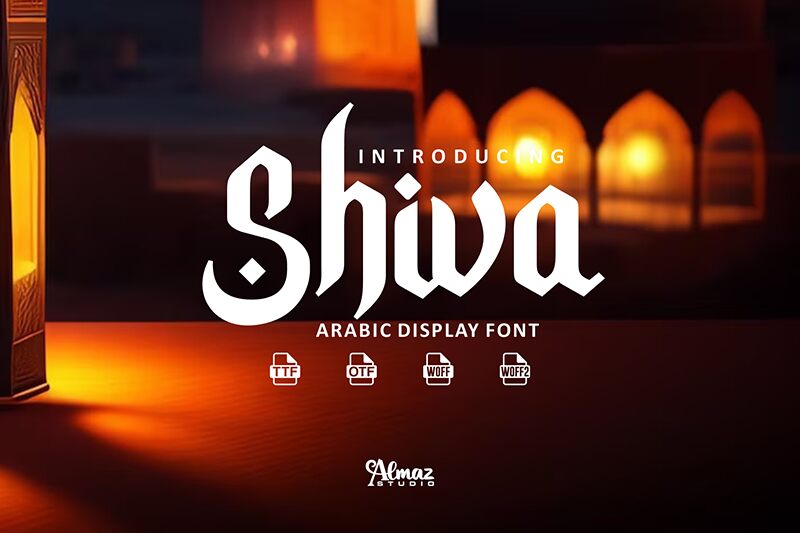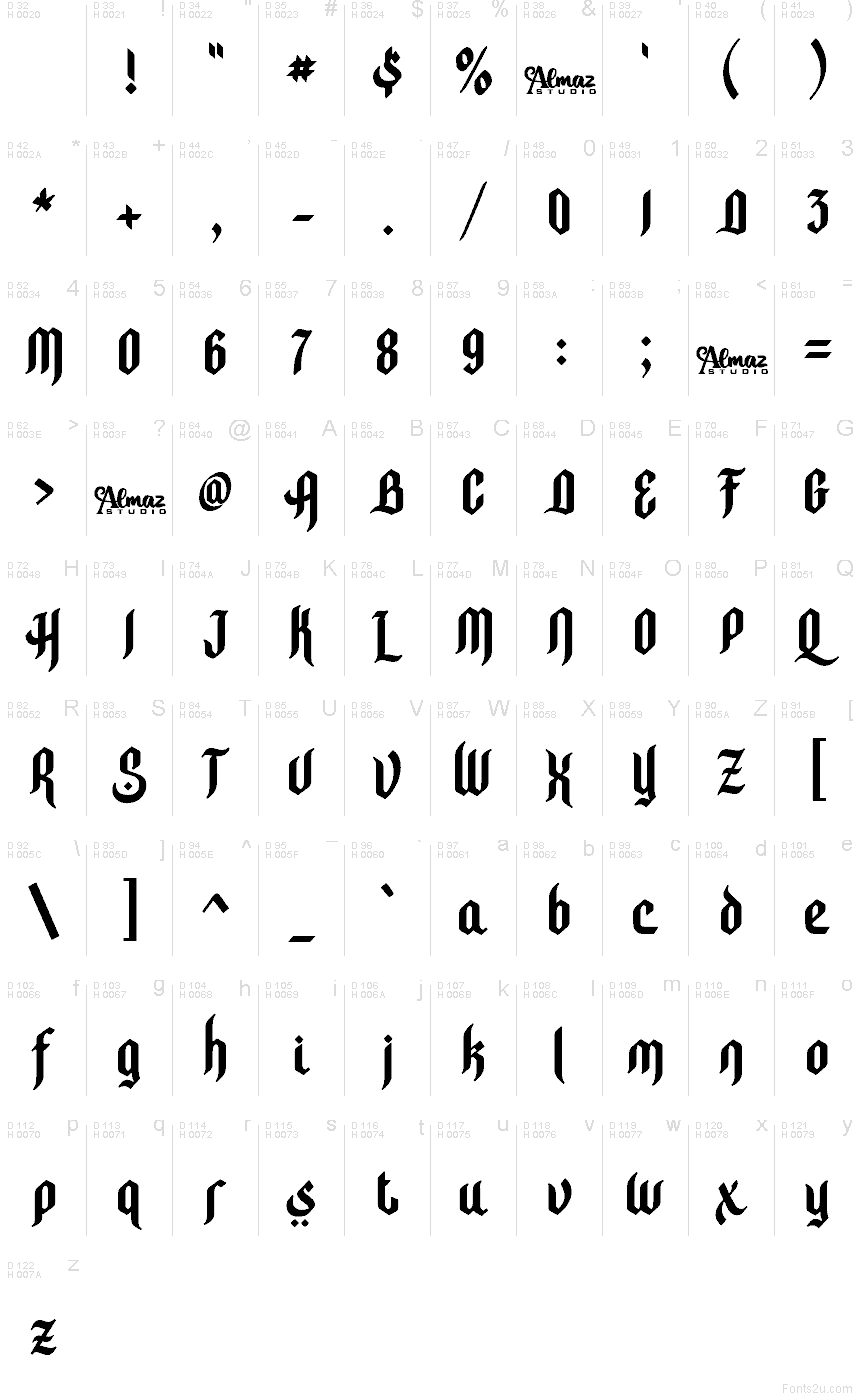
Shiva
Shiva je bezplatné blackletter písmo, ktoré charakterizujú vysoké vertikálne ťahy, ostré zárezy a kompaktný, prepletený rytmus. Vďaka nemu pôsobia písmená husto, no zároveň živo. Opakujúce sa kosočtvercové spoje a hákovité ukončenia mu dodávajú výraznú stredovekú textúru, takže dizajn pôsobí skôr kaligraficky než len dekoratívne.
Táto štruktúra robí zo Shivy skvelú voľbu pre metalové plagáty, názvy fantasy hier, obaly albumov, pivné etikety alebo branding podujatí, kde pomáha vytvoriť temnú historickú atmosféru. Písmo vynikne najmä v krátkych nadpisoch a logách, kde ostré tvary a dynamický pohyb vnútri znakov nesú atmosféru samé o sebe.